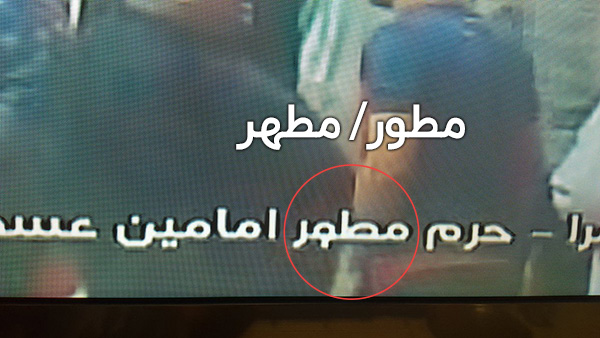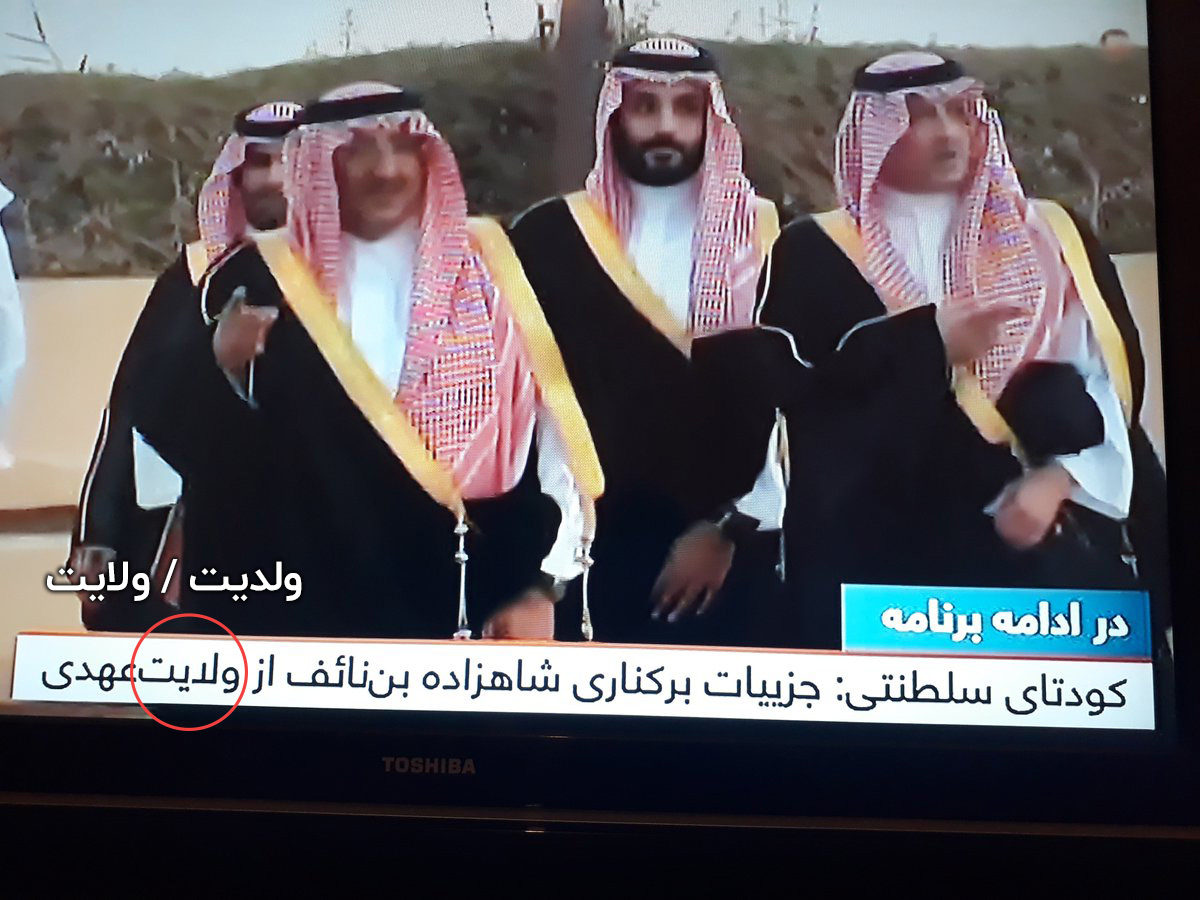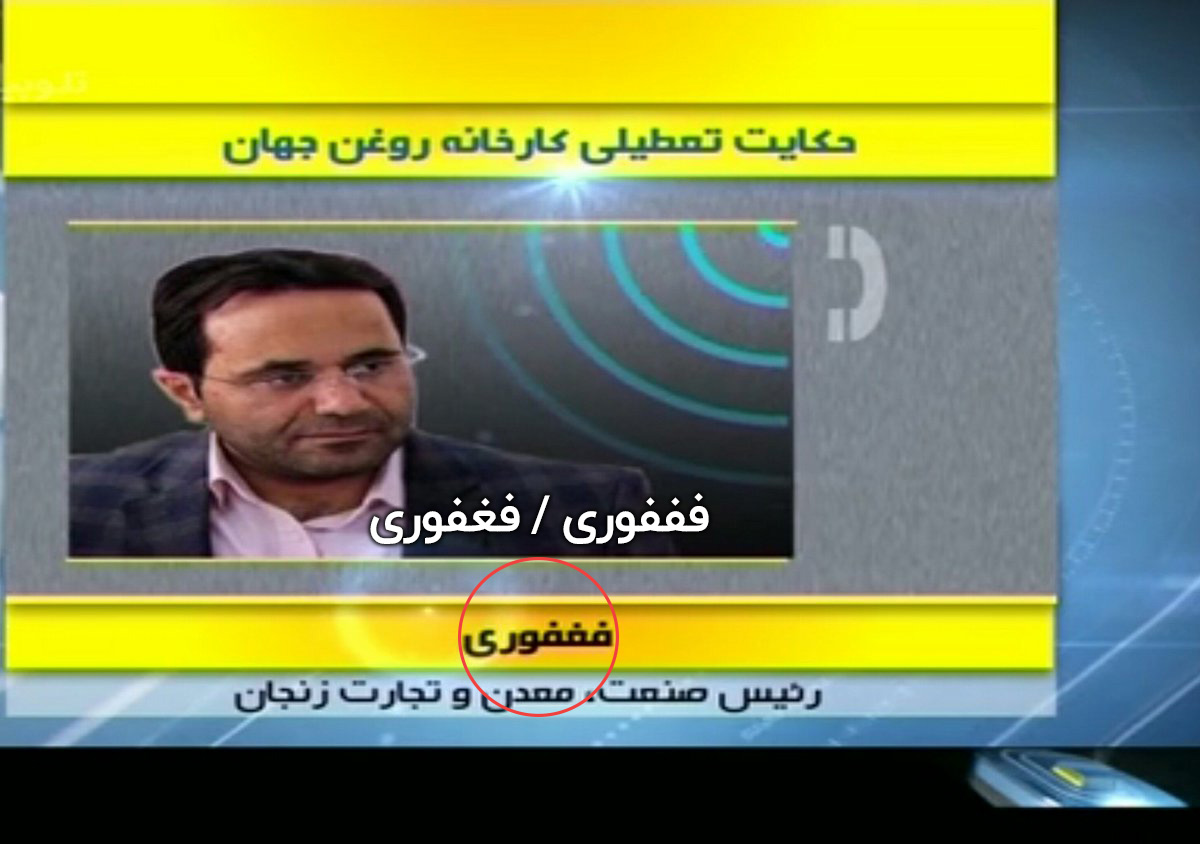
خوانايى و قابلیت خواندن (Legibility and Readability)
مدتی پیش در جریان طراحی تایپ فیس فارسی ویژه متن به تحقیقات مقدماتی نیاز داشتم در رابطه با خوانایی نوشتار. در اولین برخورد با منابع انگلیسی با این دو اصطلاح (Legibility and Readability) مواجه شدم و دانستم تعاریفی جدا از یکدیگر دارند. در حالی که ما برای نوشتار فارسی فقط از اصطلاح خوانایی استفاده می کنیم.
((خوانايى و قابلیت خواندن (Legibility and Readability) به یک معنا نیست. خوانايى قطعاً بر قابلیت خواندن اثر می گذارد و بالعکس، اما به منظور درک اینکه چگونه هر یک از این دو مقوله بر دیگری اثر گذار است، بررسی این دو به صورت جداگانه ضروری است. میزان راحت خوانده شدن یک قلم تماماً به طراح حروف بستگی دارد، در حالیکه قابلیت خواندن تا حد زیادی مسئولیت حروفچین است.
خوانايى (Legibility) میزان مشخص شدن هر حرف از دیگری است. چنین حروفی به گونه ای طراحی میشوند که خود را به شیوه ای مختصر و واضح بنمایانند که البته این امر لزوماً بدین معنی نیست که یک قلم با خوانايى زیاد، نمی تواند درطراحی خود حاوی ویژگی های خاص باشد.))
بنابر این تعریف می توان اینگونه مثال آورد که به هرمیزان در یک قلم فارسی دو حرف مشابه مانند ص و ط یا ک و گ بهتر از یکدیگر قابل تشخیص باشند. خوانايى (Legibility) در این قلم بالاتر است.
به ترتیب ۱- فونت اختصاصی شبکه۳ ۲- فونت اختصاصی اخبار شبکه یک ۳- فونت هلوتیکا عربیک (شبکه منوتو)
البته به نسبت حروف انگلیسی الفبای فارسی به طور خود به خود از تنوع شکلی بالاتری برخوردار است. کثرت حروف نقطه دار در الفبای فارسی تشخیص تفاوت حروف از یکدیگر را بیشتر می کند. که البته این موضوع به همان میزان تاثیر نحوه طراحی نقطهها در خوانایی یک فونت را نشان میدهد.
همچنین آزمایشهای ساده ای نشان داده است که خواننده هنگام مطالعه نوشتار بیشتر کلمه و ترکیبات را می خواند تا تک تک حروف را. این ویژگی در نوشتار فارسی (به دلیل پیوستگی حروف) بیشتر از لاتین خود را نشان میدهد. مدتی پیش پیامکی به دستم رسید با این مضمون:
دانشنمدان متعقدند كه مغز انسان فقط به اول و اخر كملات توجه مكينه براي هيمنه كه شما تونستی اينو بخونی.حالا ببينيد چند تا كلمه غلط بود؟
اما قابلیت خواندن (Readability) هنگامی پدید می آید که خواننده علاوه بر تشخیص تفاوت حروف از یکدیگر در مطالعه یک متن نوشتاری با مشکل روبرو نباشد و بتواند روان و سریع نوشته را بخواند که این قابلیت به مدد رعایت اصول حروف چینی پدید می آید. بسیاری از متغیر های نوشتارنگاری که در ابتدای فصل آنها را توضیح دادیم با این هدف (قابلیت خواندن (Readability)) رعایت می شوند. انتخاب قلم ، اندازه ، فاصله سطر ، ترکینگ و ترازبندی مناسب همه از مواردی هستند که قابلیت خواندن را افزایش می دهند.
«آنچه که ثابت شده این است که طی خواندن، چشم کلمات را به صورت خطی و پیوسته دنبال نمی کند بلکه طی یک سری حرکات سریع به نام جهش (saccade) با ریشه فرانسوی به معنای “لرزش بادبان” آنها را دنبال می کند. محلی که چشم به صورت لحظه بر آن توقف می کند تثبیت (fixation) نام دارد. چشم انسان معمولاً در هر ثانیه چهار یا سه تثبیت دارد. اگرچه این توقف ها کوتاه اند، تست ها نشان می دهند که در یک صدم ثانیه مغز و چشم می توانند سه تا چهار حرف و یا حتی سه تا چهار واژه کوتاه را به خاطر بیاورند.
این دامنه شناسایی و ذخیره سازی دیداری در هر تثبیت با استفاده از قلم 12 پونتی، تقریباً 10 تا 11 کاراکتر از مرکز دید است، اگر چه اطلاعاتِ طول واژه و شکل کلی آن از فاصله بیشتری قابل درک است.
به دلیل اینکه خواندن، زمانی موثرتر است که چشم بتواند در هر توقف، حروف بیشتری را شناسایی کند، اندازه قلم نباید بیش از حد مورد نیاز باشد. این سوء برداشت وجود دارد که تصور می کنیم قلم بزرگتر ساده تر خوانده می شود اما به وضوح چنین محدودیتی در مورد میزان کوچک بودن و موثر خوانده شدن نیز وجود دارد.»
اندازه بهینه قلم برای دستیابی بهتر به قابلیت خواندن به طور معمول میان 10 تا 12 پونت است.[1]
اما مسئله اندازه های استاندارد در رابطه با اندازه قلم بسیار بی معناست زیرا گرچه همه تایپ فیس ها اندازه بدنه مشترکی دارند، اما تفاوت ارتفاع دندانه هر قلم با قلم دیگرباعث می شود که کوچکتر یا بزرگتر دیده شود.
یک تایپ فیس با ارتفاع دندانه بزرگتر، بزرگتر به نظر می رسد با اینکه همه اندازه های بدنه حرف یکسان است. با این حال، میزان بیشتر ارتفاع دندانه فضای کمتری را برای حروف صعودی و حروف نزولی برجا می گذارد. با به یاد داشتن اینکه چشم ترکیب های معمول کاراکترها و شکل کلمات را می شناسد، نه حروف را، بحث می شود که حروف صعودی و حروف نزولی به شناسایی شکل کلمات، بویژه در حاشیه دامنه دید و تثبیت ها کمک می کنند. اما تایپ فیسی که ارتفاع دندانه زیاد (و بنابراین حروف صعودی و حروف نزولی ی کوچکی) دارد، تنها با ایجاد فاصله بیشتر میان سطرها بهتر عمل می کند و شمایل واضح تری از کلمات را فراهم می کند.
برای تشخیص حداکثر تعداد حروف در هر توقف چشم، آرایش متن باید فشرده تر باشد نه بازتر. فاصله گذاری یا آرایش فشرده تر متن همچنین به تشخیص شکل کلمات کمک می کند. “فشرده اما نه به هم چسبیده” مدتها درخواست حروف چینان بوده است.
تحقیق در مورد خواندن و موثر بودن طراحی متن اغلب به دلیل برخورداری از روش های تردید آمیز، تعریف های غیر دقیق از توانایی های خواننده، فقدان توجه به اثر طراحی قلم، و اثرات استانداردهای متغیر آرایش نوشتارنگاری مورد انتقاد است. اما در کل، چندین اصول بنیادی را مورد تایید قرار داده که سودمند و کاربردی است:
آرایش نزدیک به هم ، فاصله گذاری برابر میان کاراکترها ، تقریباً 10 تا 12 کلمه در هر سطر ، لدینگ کمی بیشتر برای تایپ فیس های دارای ارتفاع دندانه زیاد (و حروف صعودی و حروف نزولی کوچک) از این اصول هستند.
[1] این مقدار برای نوشتار انگلیسی تعیین شده و برای نوشتار فارسی نیاز به آزمایش ها و پژوهش های ویژه دارد.